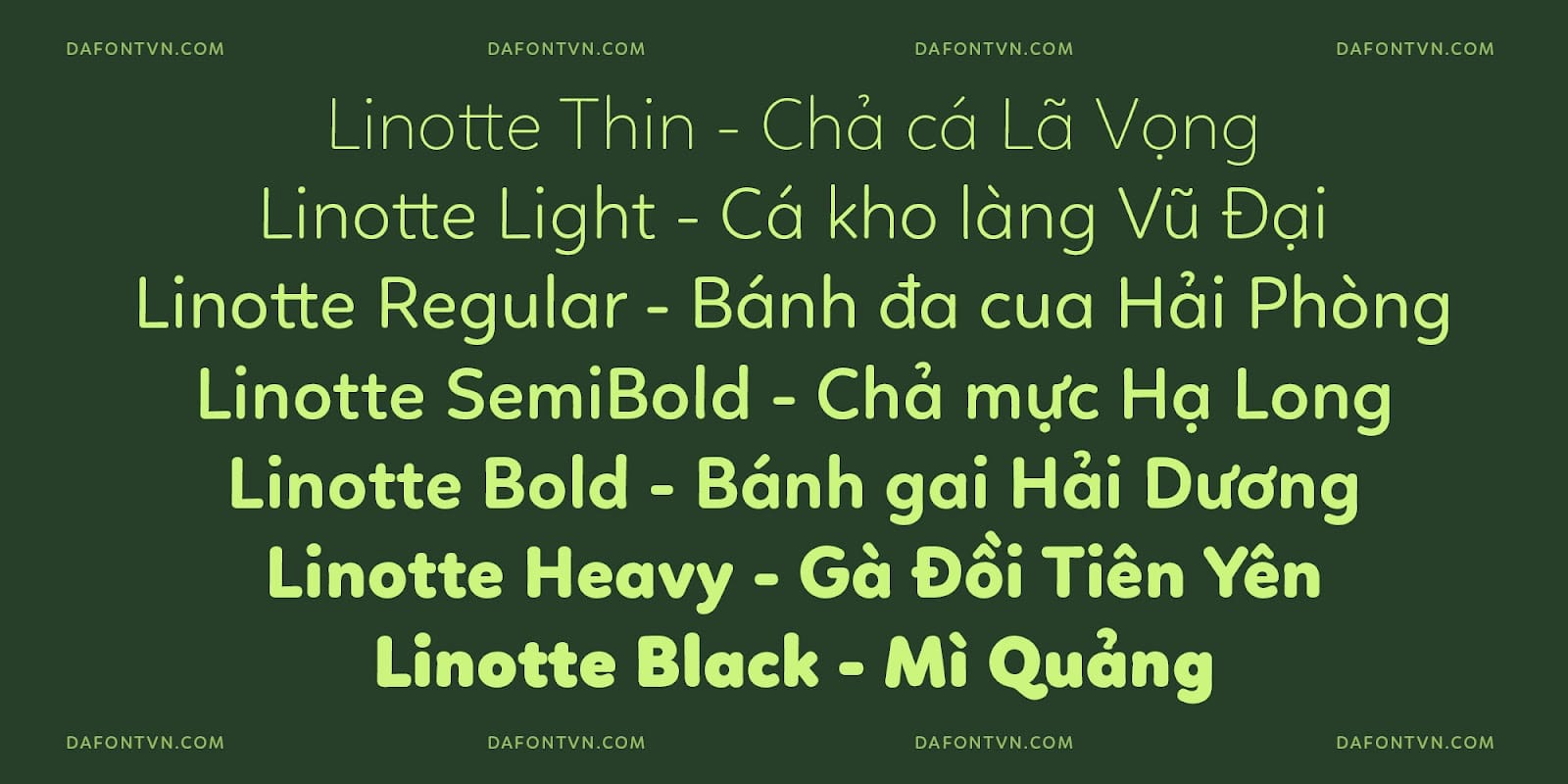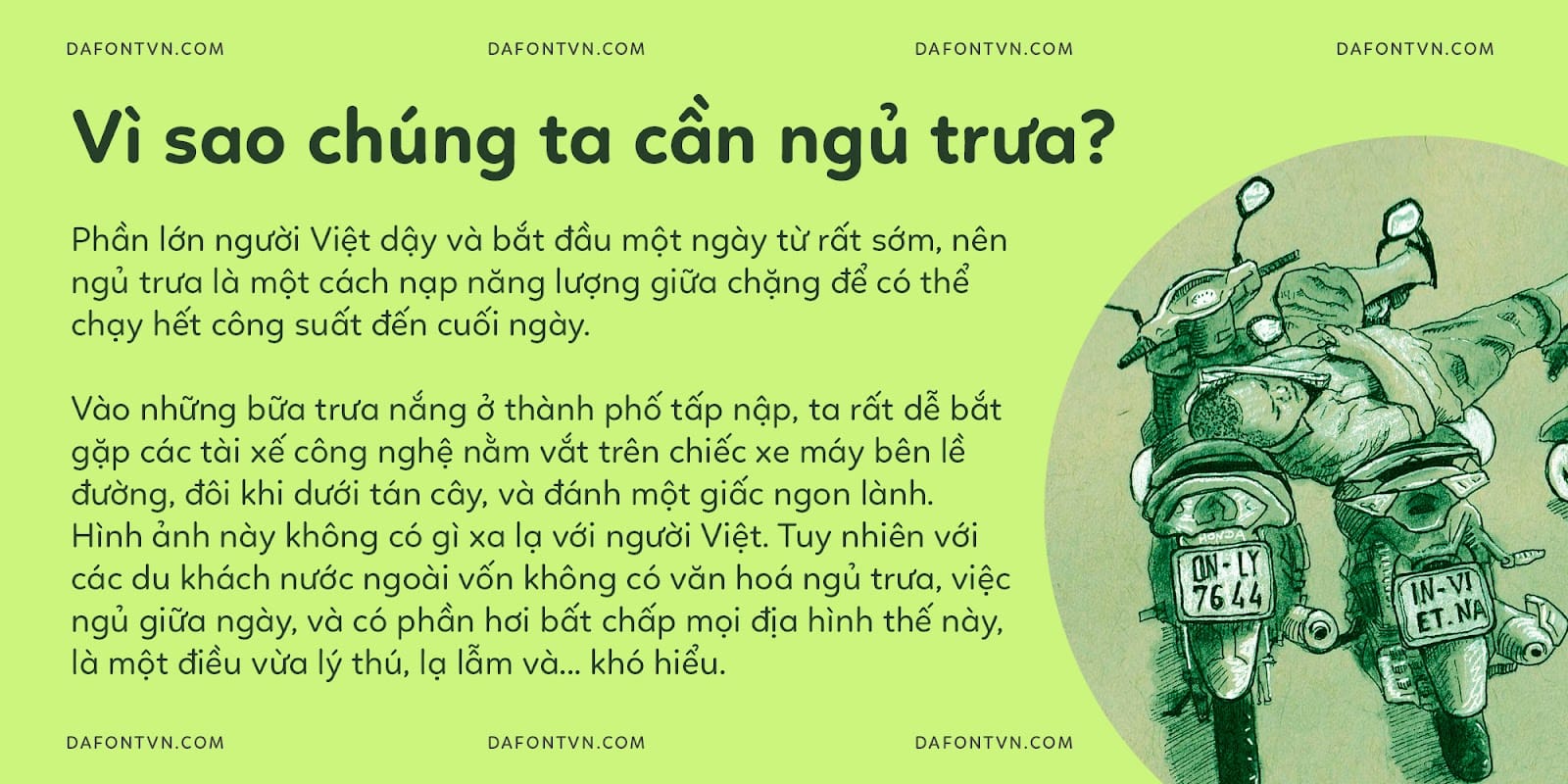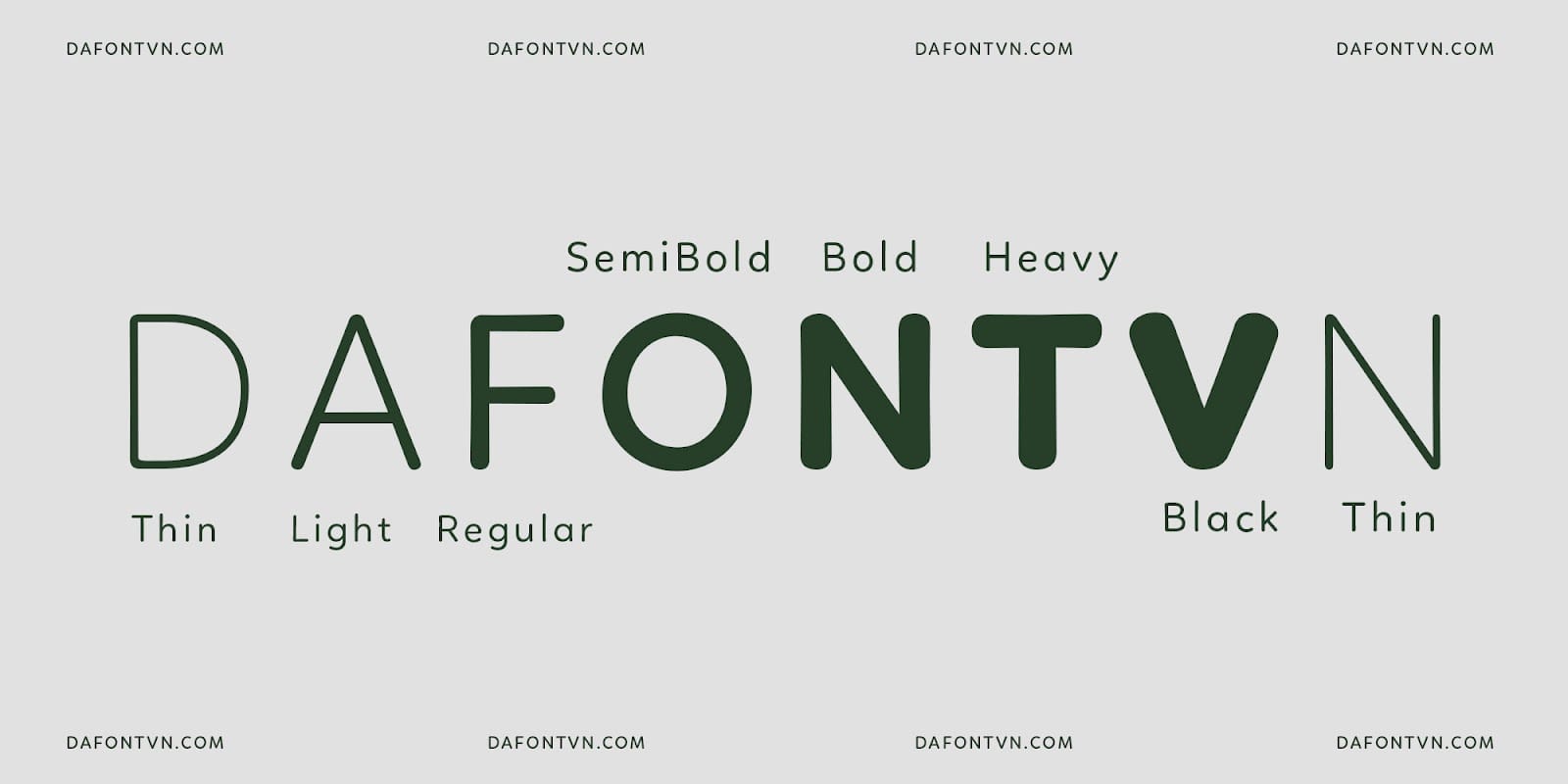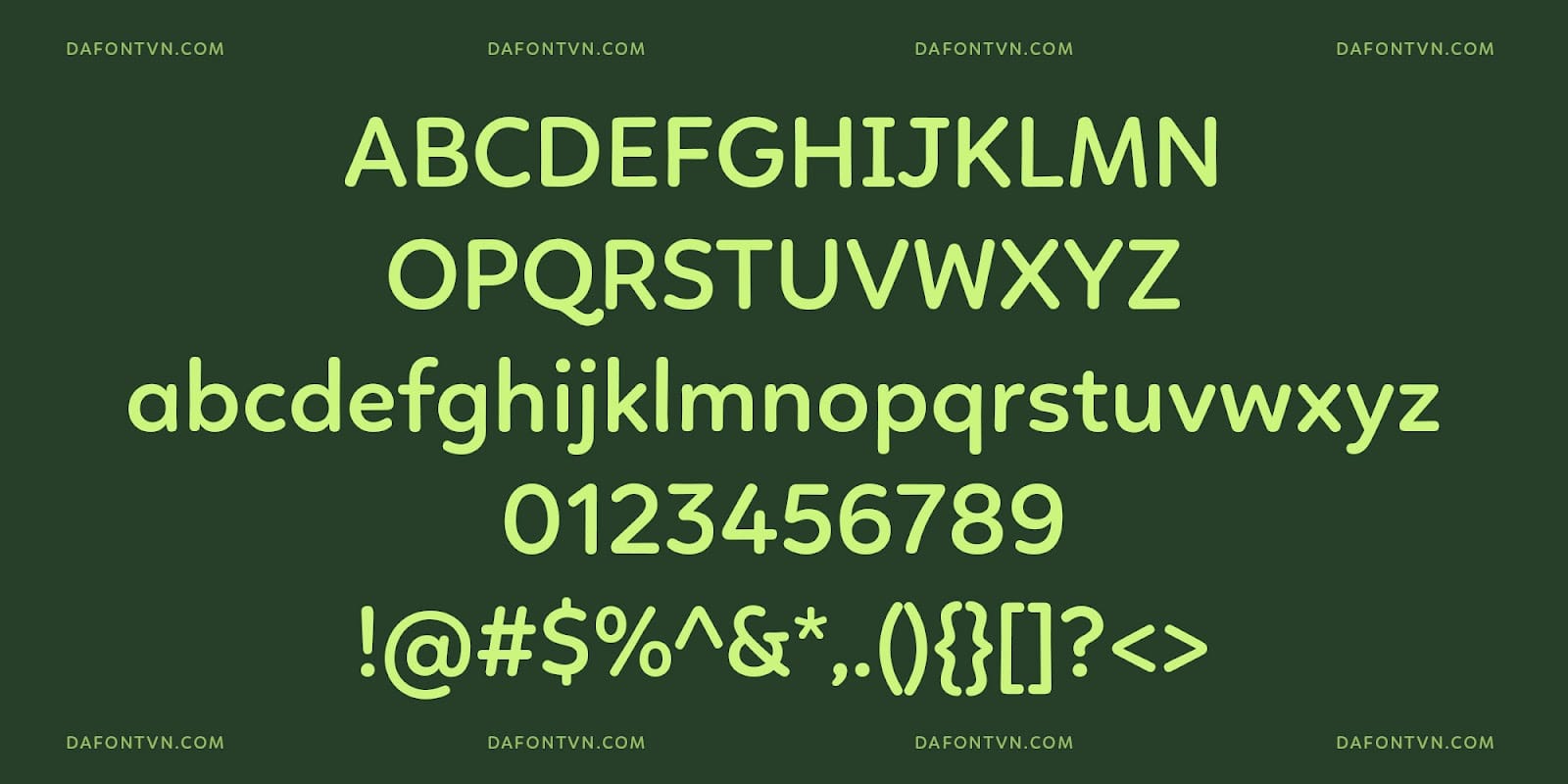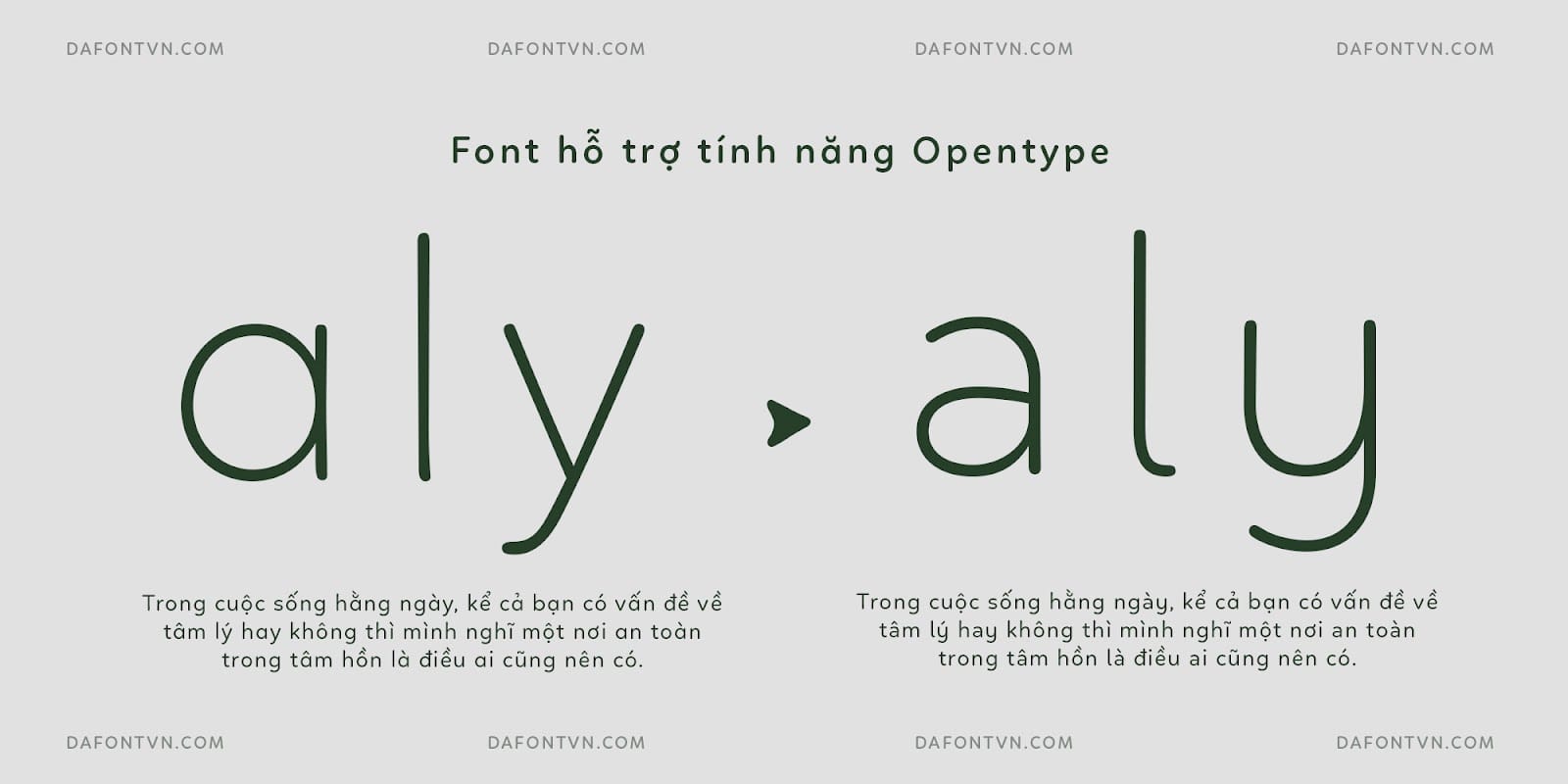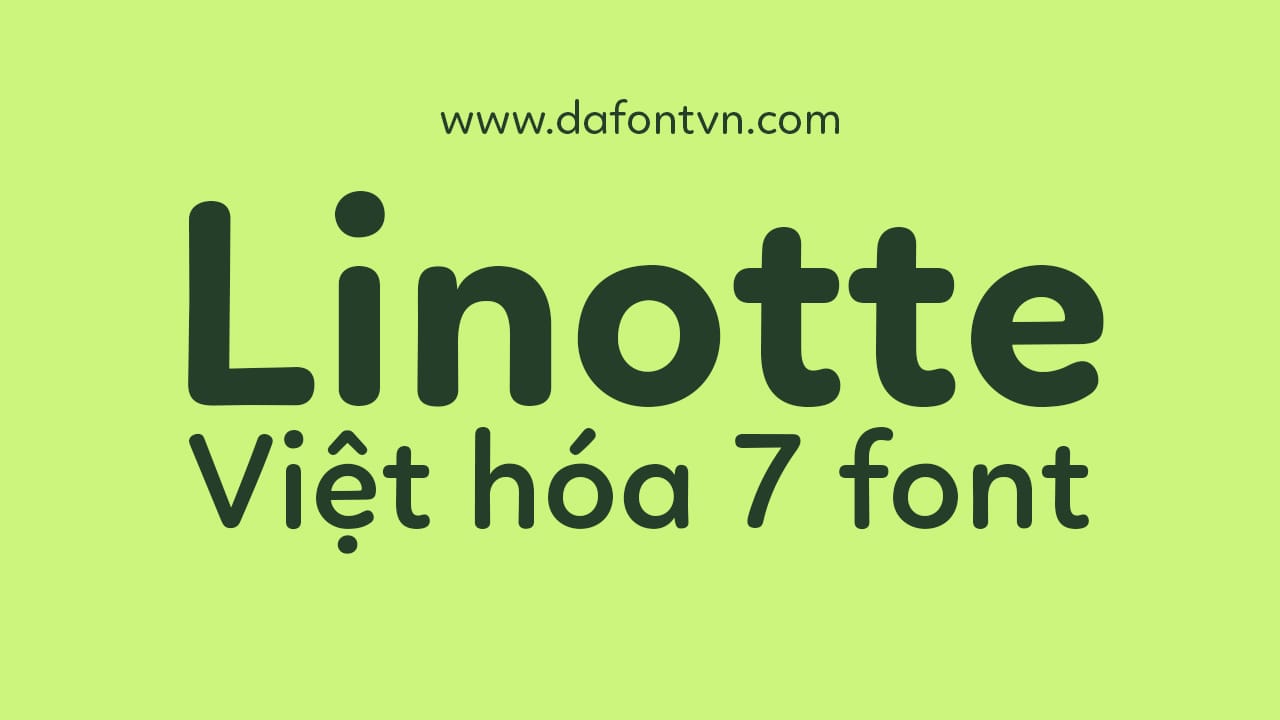
Linotte Font là một bộ font chữ bao gồm 7 kiểu với các nét tròn trịa. Những nét chữ được thiết kế ấn tượng mang lại cho kiểu chữ một cái nhìn ấm áp, ngây thơ và dễ thương, trong khi cấu trúc hình học đơn giản mang lại khả năng đọc rõ ràng trong các văn bản dài và kích thước nhỏ. Linotte là sự lựa chọn lý tưởng cho rất nhiều các thiết kế khác nhau nếu cần một kiểu chữ đẹp và hiển thị tốt ở mọi kích thước.
Được phát hành lần đầu vào năm 2014, Linotte được cập nhật vào năm 2021 với sự hỗ trợ tiếng Hy Lạp và Cyrillic, hai phong cách mới, các bổ sung và một số sửa đổi nhỏ khác. Linotte SemiBold miễn phí 100% cho mục đích sử dụng cá nhân và thương mại.
Các font chữ được cung cấp ở định dạng OpenType, bao gồm dấu phụ cho hầu hết các ngôn ngữ Châu Âu, một bộ các mũi tên và biểu tượng cũng như nhiều tính năng nâng cao bao gồm stylistic alternates, biểu mẫu phân biệt chữ hoa chữ thường, ký tự trên và dưới dòng, phân số tự động, v.v.
Đây là phiên bản Linotte việt hóa bao gồm 7 kiểu (v2.0), đã được chỉnh sửa lại một số ký tự, tối ưu, kerning đầy đủ cũng như các dấu được việt hóa chỉn chu hơn. Ngoài ra các ký tự được hoàn thiện tốt hơn trong phiên bản 2.0 này.